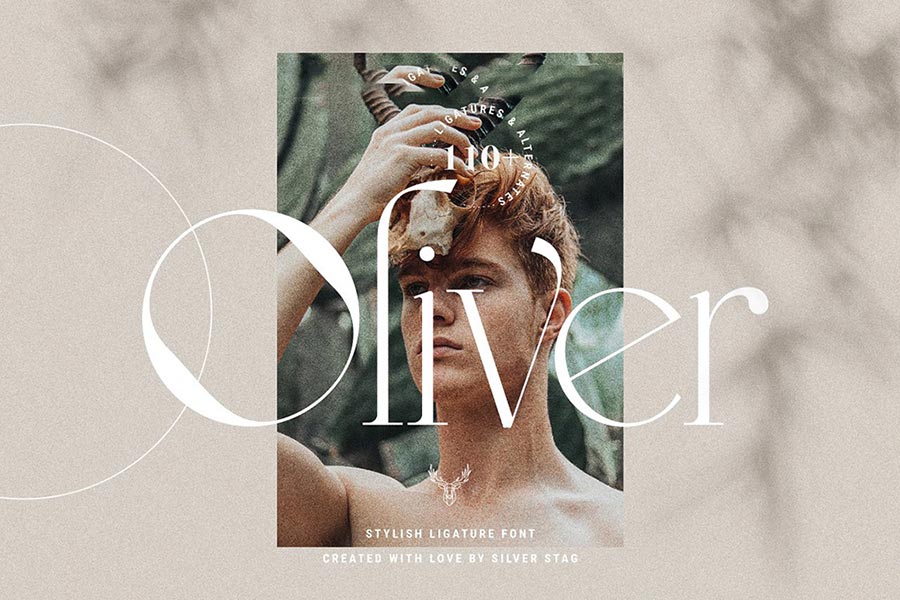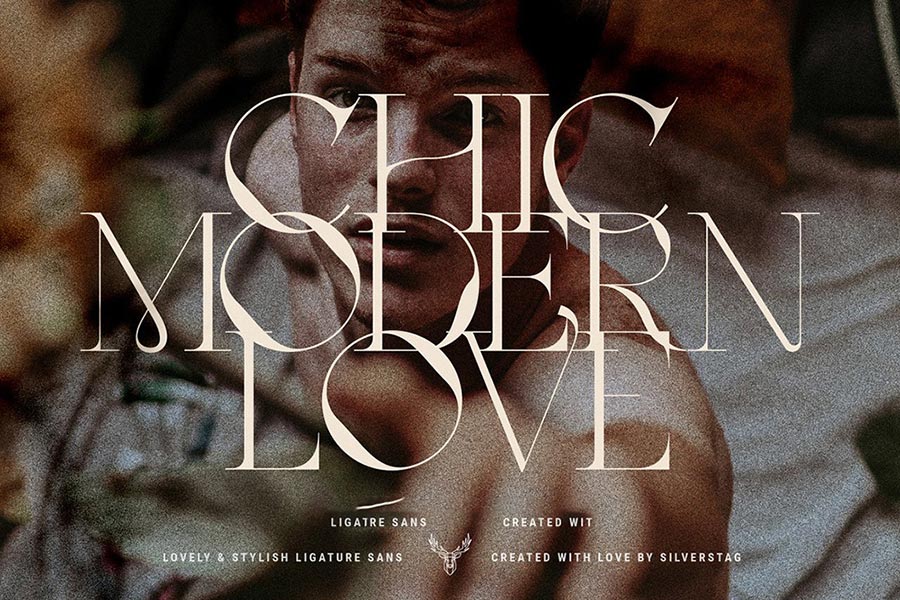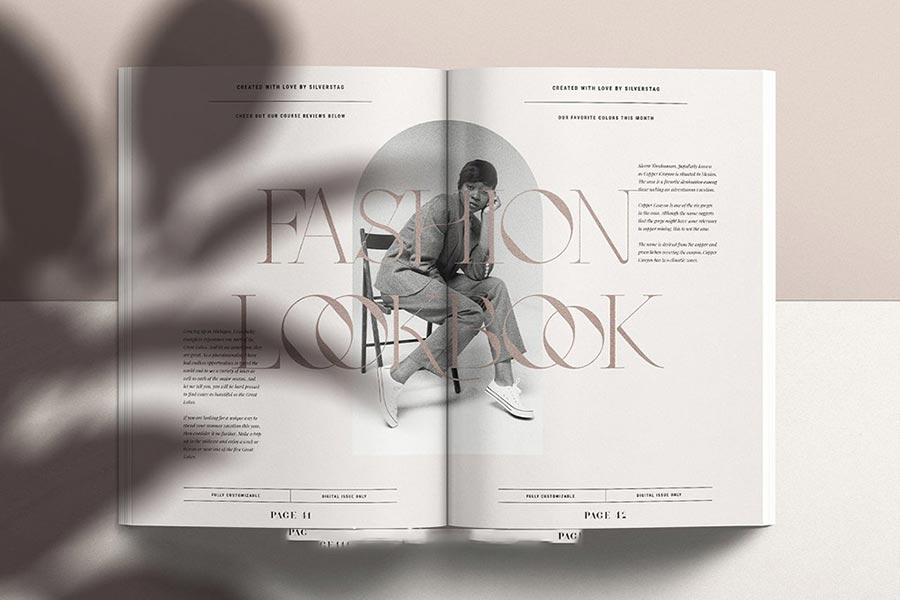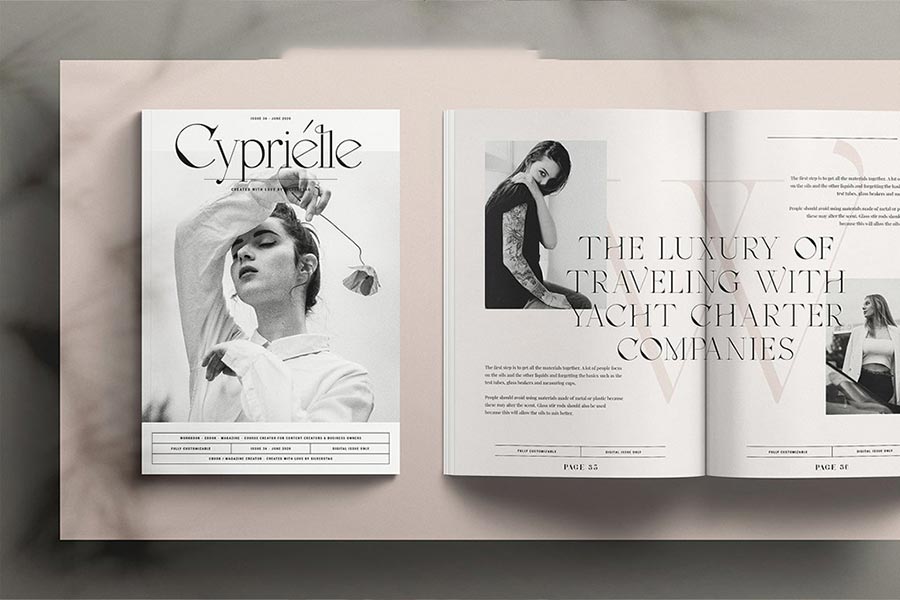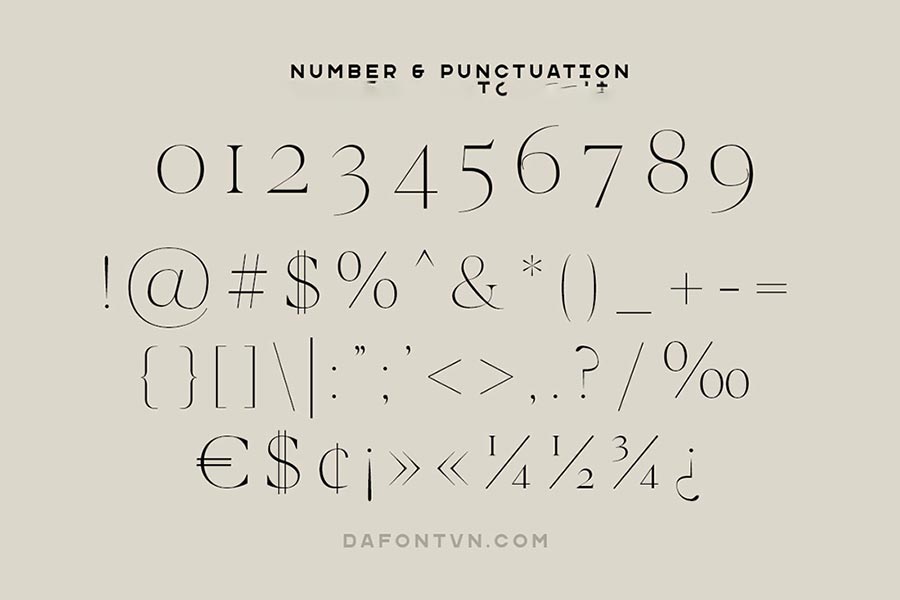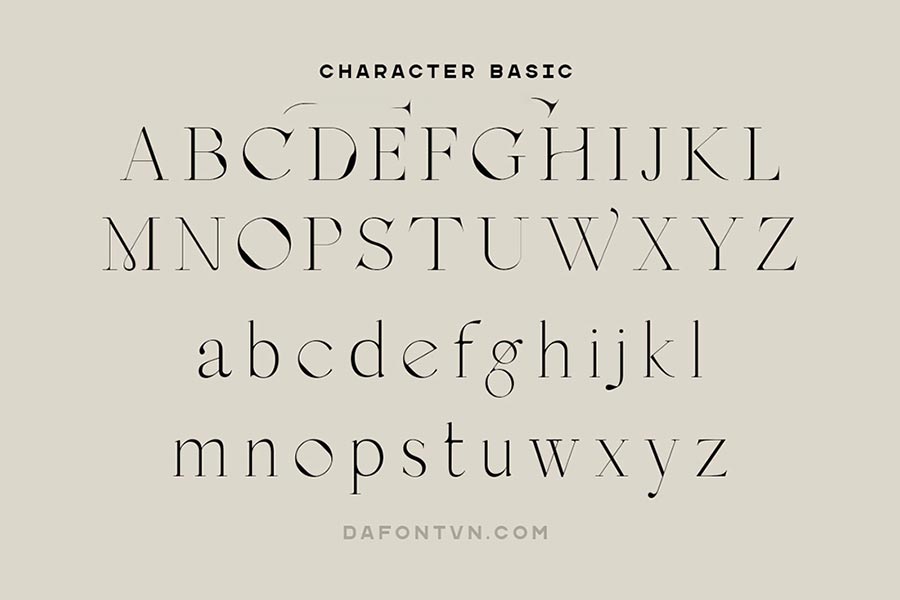
Font Việt Hóa _MOON CROWD mang đến một trải nghiệm chữ viết độc đáo với phong cách hiện đại và dễ sử dụng. Được thiết kế với nhiều đặc điểm nổi bật, font chữ này phù hợp với những dự án thiết kế sáng tạo. Sadesign.vn chia sẻ miễn phí bộ font này, giúp các designer có thể tạo ra những sản phẩm độc đáo mà không cần phải lo lắng về vấn đề bản quyền. Hãy cùng tìm hiểu cách tải và ứng dụng font _MOON CROWD vào các thiết kế của bạn.
1. Giới Thiệu Về Font Việt Hóa _MOON CROWD
Font Việt Hóa _MOON CROWD là một trong những font chữ được ưa chuộng trong cộng đồng thiết kế, đặc biệt là trong các dự án yêu cầu sự sáng tạo và hiện đại. Với kiểu chữ mềm mại, uyển chuyển và dễ đọc, font _MOON CROWD mang đến cảm giác dễ chịu cho người nhìn, đồng thời thể hiện sự tinh tế và chuyên nghiệp. Font này được tối ưu hóa cho cả tiếng Việt và các ngôn ngữ khác, giúp bạn dễ dàng sử dụng trong mọi dự án thiết kế.
Bộ font _MOON CROWD này không chỉ có các ký tự Việt hóa đầy đủ mà còn giữ được các yếu tố đặc trưng của font gốc, tạo nên sự cân đối và hài hòa trong mỗi thiết kế. Bạn có thể sử dụng font này cho nhiều mục đích, từ thiết kế thiệp mời, quảng cáo đến các dự án truyền thông trên nền tảng kỹ thuật số.
2. Tính Năng Nổi Bật Của Font _MOON CROWD
1. Phong Cách Thiết Kế Tinh Tế và Độc Đáo
Font _MOON CROWD mang đến vẻ đẹp hiện đại và thanh thoát, với các đường nét mềm mại, uốn lượn tạo nên sự lôi cuốn ngay từ cái nhìn đầu tiên. Đây là một font chữ rất phù hợp với những thiết kế mang tính chất nhẹ nhàng, thanh thoát nhưng vẫn đảm bảo độ nổi bật trong các ấn phẩm đồ họa.
2. Việt Hóa Hoàn Chỉnh
Một điểm nổi bật của font _MOON CROWD là bộ ký tự Việt hóa hoàn chỉnh, giúp các designer có thể sử dụng trực tiếp cho các dự án liên quan đến ngôn ngữ tiếng Việt mà không cần phải lo lắng về sự thiếu sót các ký tự đặc biệt như dấu câu hay các chữ cái có dấu. Điều này đặc biệt quan trọng khi bạn cần thiết kế các ấn phẩm quảng cáo hoặc truyền thông phục vụ cho thị trường Việt Nam.
3. Dễ Dàng Tùy Chỉnh và Sử Dụng
2. Tăng Tính Sáng Tạo Cho Dự Án Thiết Kế
Với font _MOON CROWD, bạn có thể tự do sáng tạo và ứng dụng vào nhiều loại dự án khác nhau. Từ những thiết kế đơn giản như thiệp cưới, thiệp mời, poster quảng cáo, đến các sản phẩm phức tạp hơn như website, logo hay các thiết kế truyền thông đều có thể dễ dàng áp dụng font này. Font _MOON CROWD đem lại một sự hài hòa giữa tính sáng tạo và tính thực tế trong các thiết kế.
3. Tăng Độ Thẩm Mỹ Cho Các Ấn Phẩm Đồ Họa
Nhờ vào kiểu dáng thanh thoát và sang trọng, font _MOON CROWD giúp tăng độ thẩm mỹ cho các sản phẩm thiết kế. Dù bạn thiết kế poster sự kiện, banner quảng cáo, hay các sản phẩm truyền thông kỹ thuật số, font chữ này sẽ tạo nên sự nổi bật và dễ đọc, giúp thu hút sự chú ý của người xem.
4. Kết Luận
Font _MOON CROWD từ Sadesign.vn là một tài nguyên tuyệt vời cho các designer muốn tìm kiếm một font chữ Việt hóa đẹp và dễ sử dụng. Với thiết kế hiện đại, tinh tế và miễn phí, bộ font này phù hợp với nhiều loại dự án khác nhau, từ thiệp cưới, poster quảng cáo đến các thiết kế truyền thông kỹ thuật số. Hãy tải ngay font chữ _MOON CROWD để làm phong phú thêm bộ sưu tập tài nguyên thiết kế của bạn và tạo ra những sản phẩm ấn tượng!